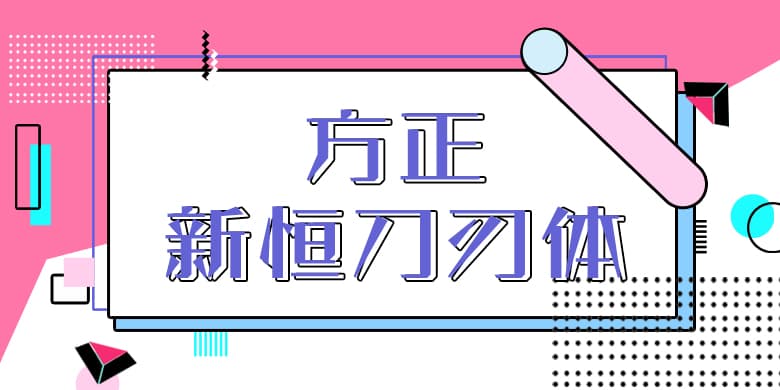
品牌:方正字库设计师:孙新恒发行时间:2021字库编码:大陆简体(GB2312-80)分类:创意字体字体属性:精品字
方正新恒刀刃体是在老式板报类字体的基础上进行改良规范的,该字体所有笔画全部以直线表现,撇、捺、点、勾收尾处均采用切角处理,似刀头、似利刃,故取名刀刃体,是一款既有力量感,又有活跃感,既有民国时期的风格,又具备新时代气息的字体。适用于海报招贴、视频媒体、产品包装、书籍报刊及周边领域。